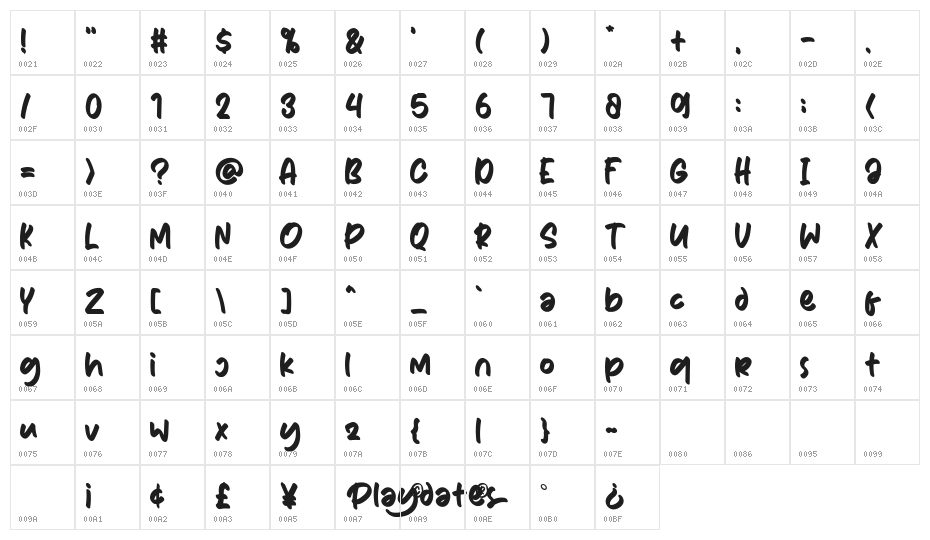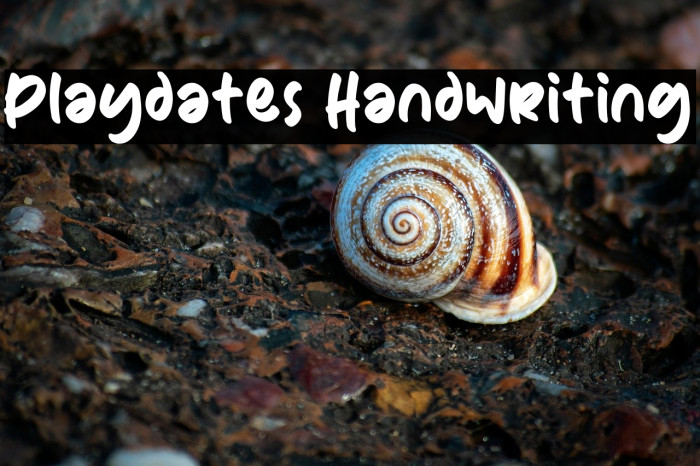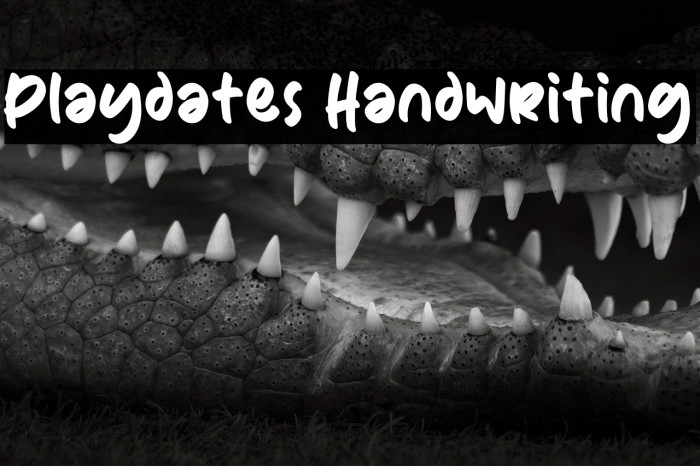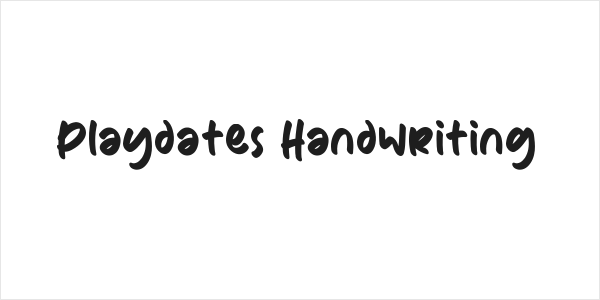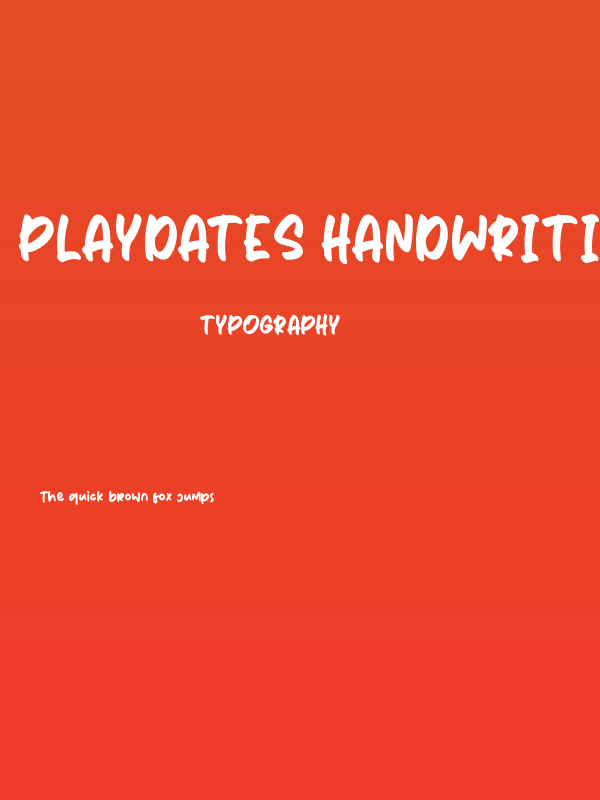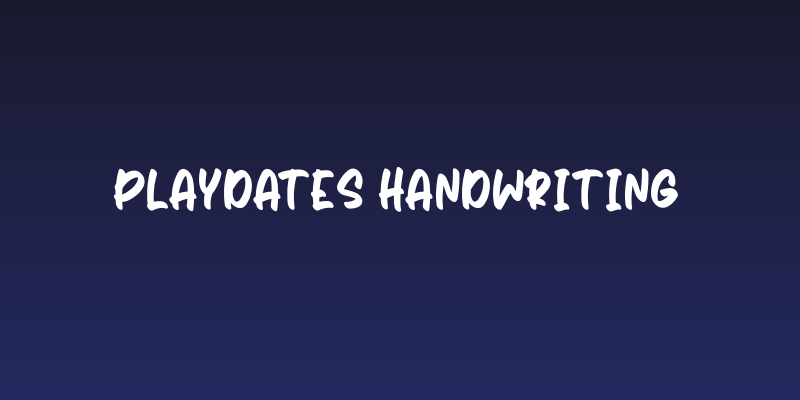
Playdates Handwriting Font
| Nome | Playdates Handwriting |
| Stile generale | Playful, Casual |
| Caso d'uso | Headlines, Logos, Invitations |
| Progetti proposti | Ideal for children's books, playful branding, creative invitations, and casual social media graphics. |